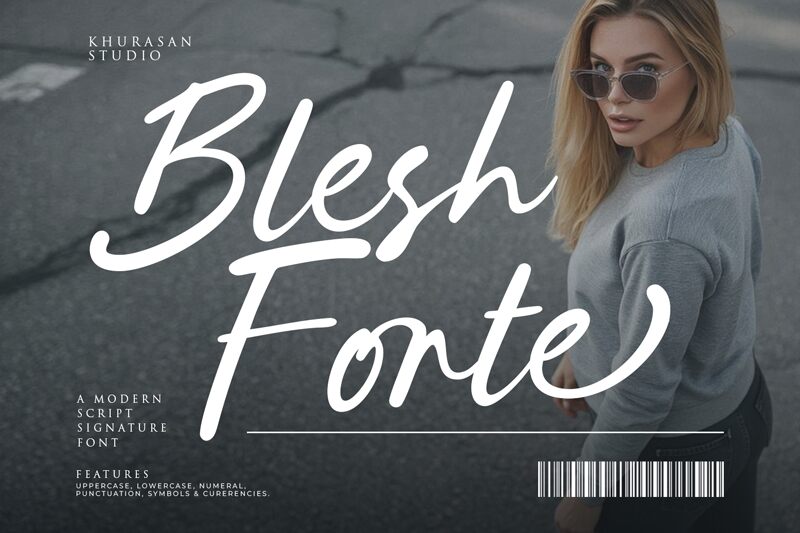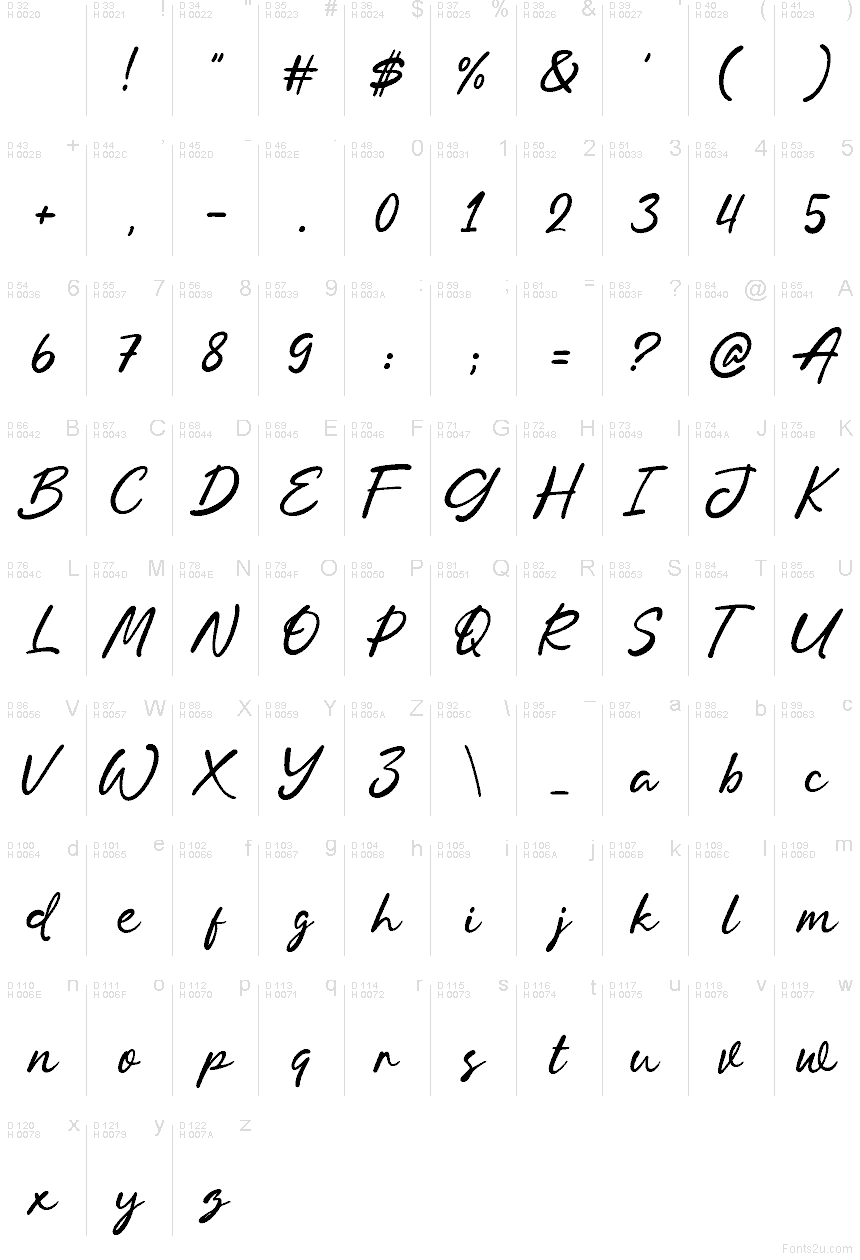
Blesh Forte od Khurasan je bezplatné ručně psané písmo ve stylu štětce s volným, svižným rytmem. Písmena plynou vpřed s dlouhými tahy, pružným náklonem a zaoblenými křivkami, které fontu dodávají ležérní, fluidní a lehce dramatický nádech.
Hodí se pro branding kosmetických značek, obaly na kávu, citáty na sociální sítě, svatební tiskoviny nebo přebaly hudebních alb, kde je potřeba, aby písmo působilo živě. Použijte ho pro krátké nadpisy, loga ve stylu podpisu, titulky nebo výrazné citace, zejména pokud chcete, aby text působil osobně a nebyl příliš strojený.
Blesh Forte